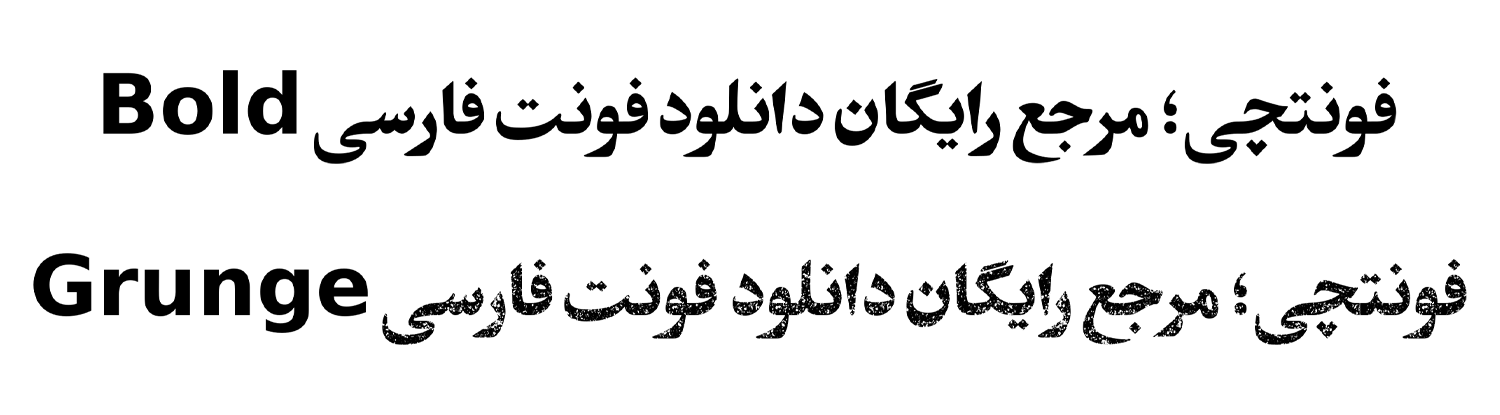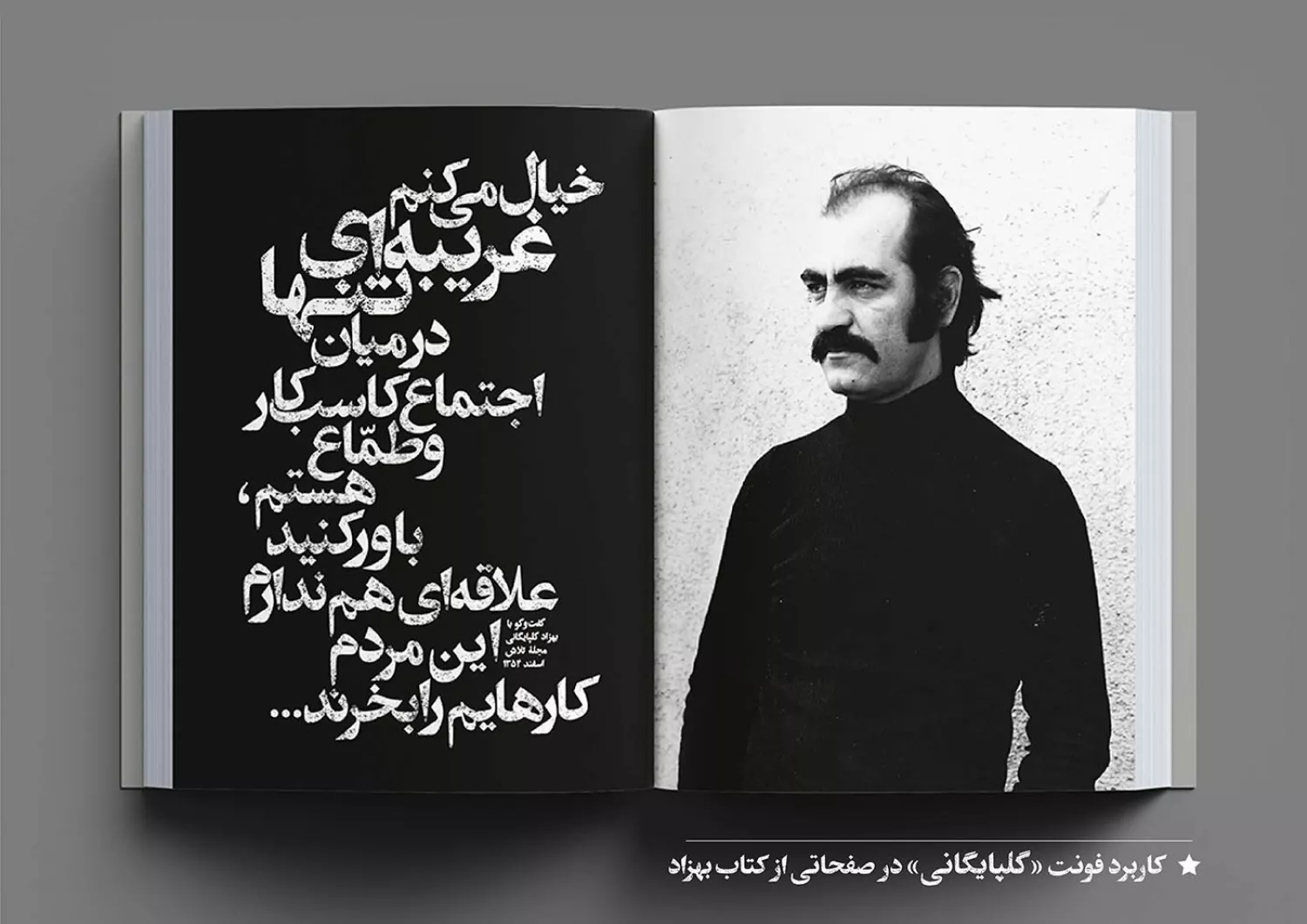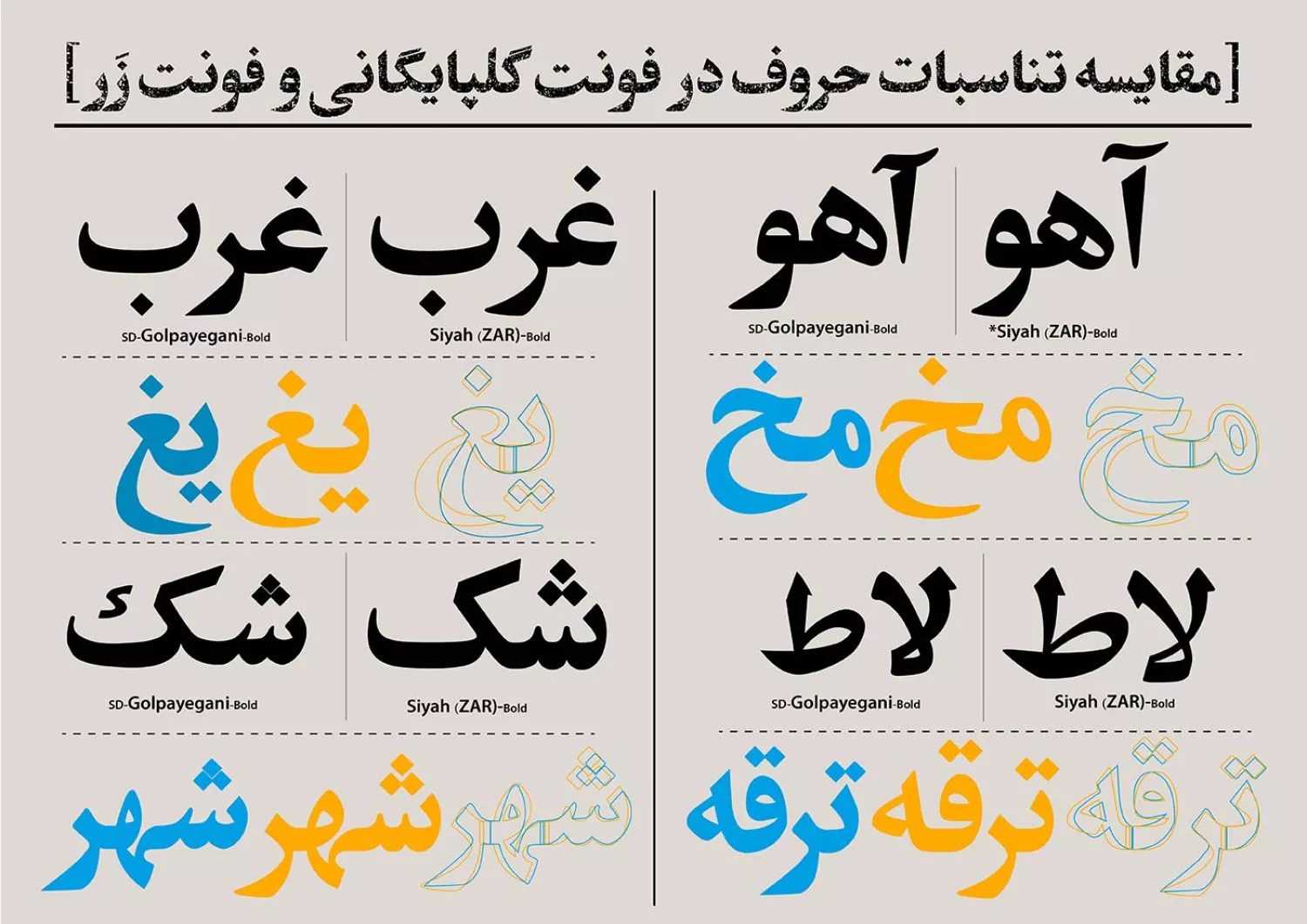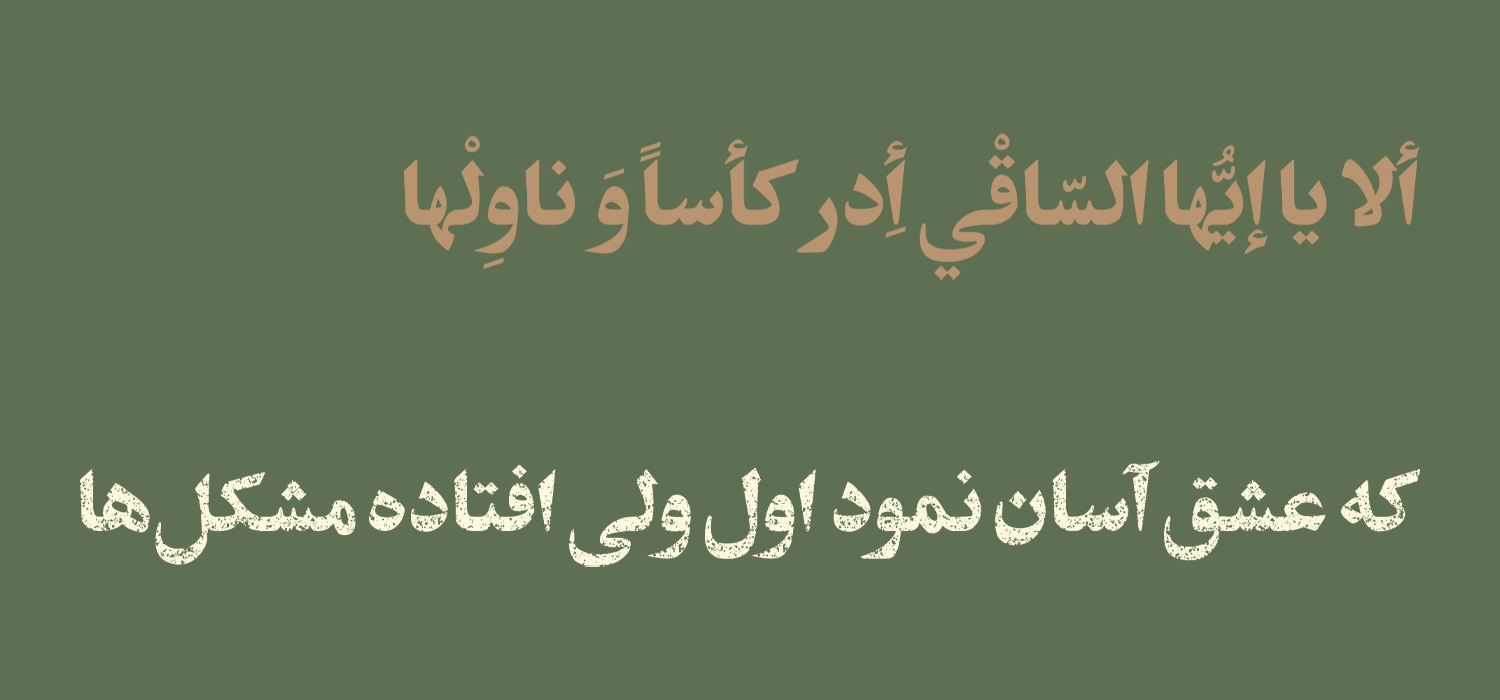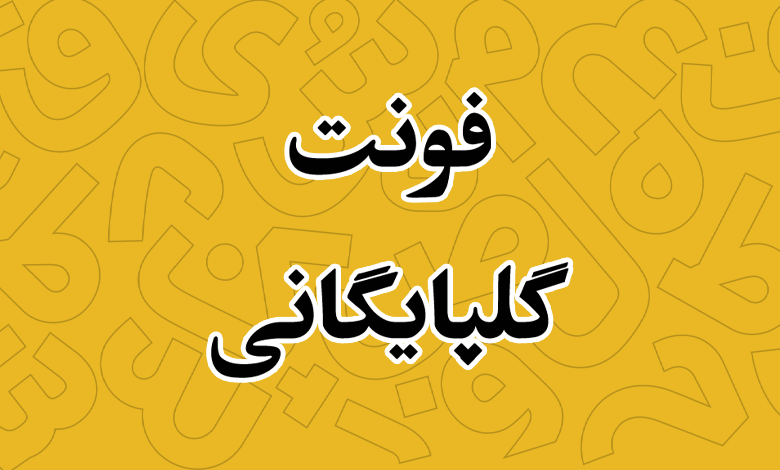
فونت گلپایگانی (Golpayegani)
این فونت توسط حجت نورالهی و به سفارش استودیو دفتر در دو سبک ساده و بافتدار (گرانج) طراحی شده است. نسخه ای بازسازی شده بر اساس آثار بهزاد گلپایگانی (۱۳۱۷-۱۳۶۴) است که وی را یکی از مهمترین و موثرترین پایهگذاران تایپوگرافی فارسی در تاریخ گرافیک ایران میشناسند.
در ادامه این نوشته از سایت دانلود فونت فونتچی، به نقد و بررسی فونت گلپایگانی خواهیم پرداخت؛ قلمی که با طراحی خاص خود میتوانید از ان در کارهای گرافیکی حوزه تبلیغات یا صنایع چاپ بهویژه چاپ جلد کتب استفاده کنید که بهترین اثرگذاری را در این دو حوزه دارد.
بررسی و دانلود فونت گلپایگانی (Golpayegani)
پیش از هر چیزی بد نیست نگاهی به تاریخچه ایجاد این قلم بپردازیم. بهزاد گلپایگانی، طی سالهای فعالیتش در «انتشارات فرانکلین»، برای اولین بار مجموعهای از طرح جلدها را بر پایه تایپوگرافی طراحی کرد. وی نوشتههای آثارش را از روی حروف «سیاه» (زَر) الگوبرداری میکرد. در طی فرآیند طراحی، تناسبات و شکل حروف دگرگون میشدند و در نهایت فرمهایی تازه پدید میآمدند.
فونتی که امروزه به نام «فونت زر» میشناسیم در دوران فعالیت وی (دهههای ۵۰، ۶۰ و قبل از آن) با نام حروف سیاه در وزنهای ۱۲، ۲۴، ۳۶، ۴۸ و ۷۲ پوینت شناخته میشد. در دهه ۷۰ با ورود رایانه به ایران و نشر دیجیتال، واژه نامه سینا به زر تغییر نام پیدا کرد.
برای بازسازی «فونت گلپایگانی» حروفی که در این فرآیند بیشتر دچار دگرگونی (Deformation) شده بودند، استخراج شده و در ترکیب نهایی قرار داده شدند.
سبک طراحی و وزن فونت گلپایگانی
سبک طراحی این فونت بر اساس خط نسخ است. حروف دارای وزن بولد و نسبتا سیاه هستند که با توجه به فواصل نامنظمی که در سرتاسر بخشها برای حروف وجود دارد، شاهد فونتی نسبتا فشرده و درشت هستیم.
تناسب حروف فونت گلپایگانی در مقایسه با فونت سیاه زر، تغییرات عمدهای داشته است که از جمله آنها فشردهتر شدن حروف، چسبیدن کلاه حرف «آ» به الف، ریزتر شدن چشمیها و دخالت بیشتر خط نسخ در دندانهها از جمله این موارد هستند.
پشتیبانی کامل از زبان فارسی و عربی
فونت گلپایگانی از دو زبان فارسی و عربی پشتیبانی کاملی دارد. این قلم که بر اساس آثار بهجای مانده از بهزاد گلپایگانی طراحی شده، تمامی حروف مشترک این دو زبان را داشته و در حروفی همچون «ک، ی، ه، ؤ، ئ» عربی که متفاوت از زبان فارسی هستند، گلیفهای اختصاصی را پشتیبانی میکند.
با اینکه کلیه حروف بر اساس رسم خط فارسی هستند که میتواند برای استفاده در سایر زبانهای کردی و ترکی نیز مناسب باشد؛ اما ممکن است هنگام استفاده از برخی ترکیبات و حروف نامنظمی هایی برای این زبانها وجود داشته باشد. ولی در حالت کلی پشتیبانی از این دو زبان را به لطف یکسان بودن رسم خط نیز پشتیبانی میکند.
اعراب در این قلم نیز استاندارد بوده و هنگام قرارگیری در کنار سایر اعراب نمایشی مثل تشدید، همزه و سکون موجب بههم ریختگی حروف یا چسبیدن اعراب اصلی به حروف قبل و بعد نخواهد شد.
علاوه بر این، اعداد فارسی و عربی متناسب با زبان انتخابی پشتیبانی میشود. اعدادی مثل «۴۵۶» عربی که در مقایسه با اعداد «۴۵۶» فارسی که ظاهری متفاوت دارند در این قلم پیادهسازی شده و دارای گلیف استاندارد خود هستند تا موجب ناهماهنگی متن شما برای زبان دیگر نشود.
مناسب حوزه تبلیغات و چاپ
همانطور که در جایجای این نوشته ذکر کردیم، بهترین کاربرد فونت گلپایگانی برای صنعت تبلیغات و چاپ است. از این فونت، خصوصا سبک گرانج میتوانید در حوزه تبلیغات فیزیکی در بیلبوردهای شهری و تابلوهای اعلان استفاده کنید تا کلمات کلیدی که نیازمند درگیر کردن ذهن مخاطب است را با این قلم تایپ کنید.
علاوه بر این میتوانید در صنعت چاپ، خصوصا طراحی جلد کتاب از این قلم که وزن بولد و سیاهی دارد استفاده کنید که به توجه بیشتر مخاطب برای خرید چنین کتابهایی منجر خواهد شد. کاربردهای این قلم محدود به این موارد نیست؛ اما با توجه به تاریخچه و حس نوستالژی که دارد بهترین اثر را در چنین مواردی از خود برجای خواهد گذاشت.
از جمله دیگر کاربردهای این قلم میتوان به ساخت انواع پوستر بهویژه پوستر موسیقی و فیلم اشاره کرد که با تم قدیمی و نوستالژی باشند.
این فونت برای استفاده در متنهای کوتاه و عناوین مناسب است. از همینرو وزن متفاوت این قلم در مقایسه با فونت کلی سایت که وزن معمولی دارد، موجب جلب توجه در این بخشها شده و نگاه مخاطب را بیشتر درگیر خواندن خواهد کرد.
خصوصا اینکه در سایتهای فروشگاهی نیز میتوانید با طراحی اسلایدر و بنر با استفاده از ساختار بافتدار این قلم، تفاوت بیشتری را قائل شوید تا مخاطبان را درگیر بررسی محصولات خود کنید.
استفاده از چنین قلمهای ترکیبی در سایت که یک فونت ضخیم و معمولی را ایجاد کنند، به دلیل نوع تفاوتاولیه از نظر وزن و ظاهر باعث جلب توجه مخاطب میشوند. حتی اگر مخاطب دقیقا در حال مطالعه نوشته نباشد، صرفا نگاه سرسری به متن محتوا و وزن متفاوت باعث جلب توجه خواهد شد. خصوصا در سایتهایی با محتوای بلند که به خواننده در خوانش بهتر و گم نشدن بین پاراگرافهای مختلف نیز کمک خواهد کرد.